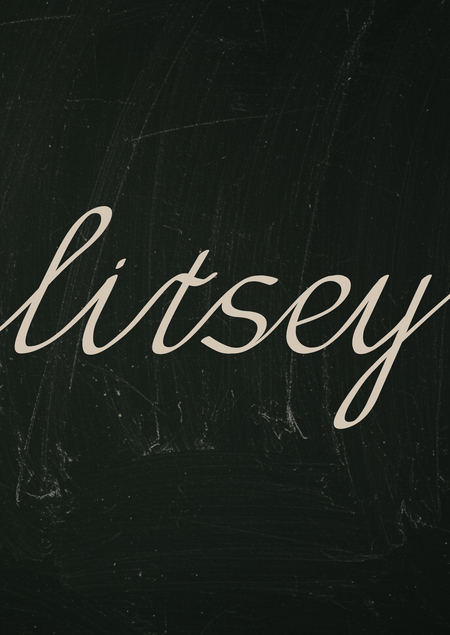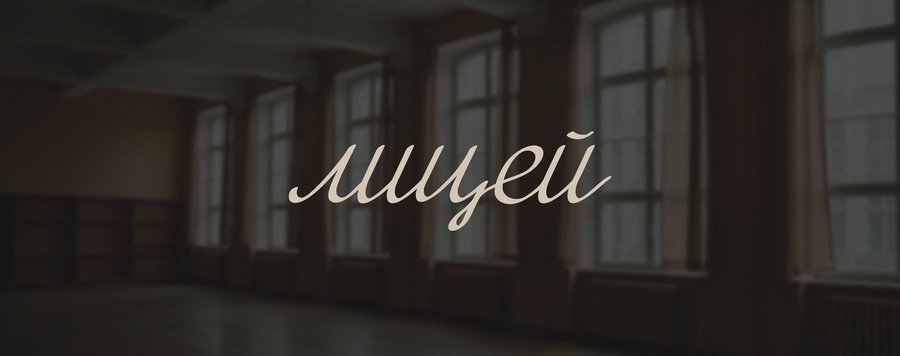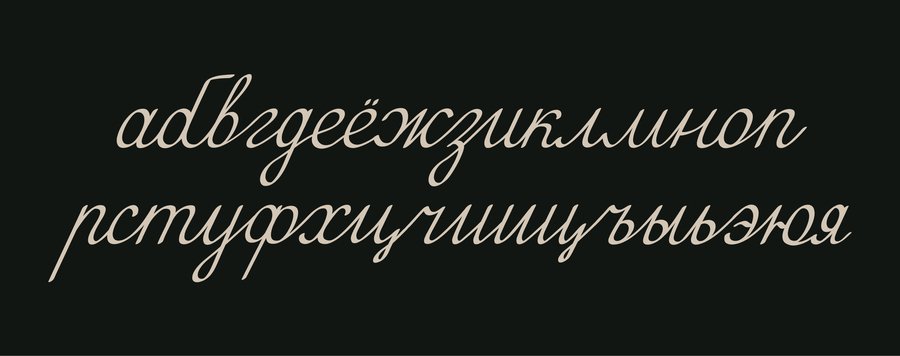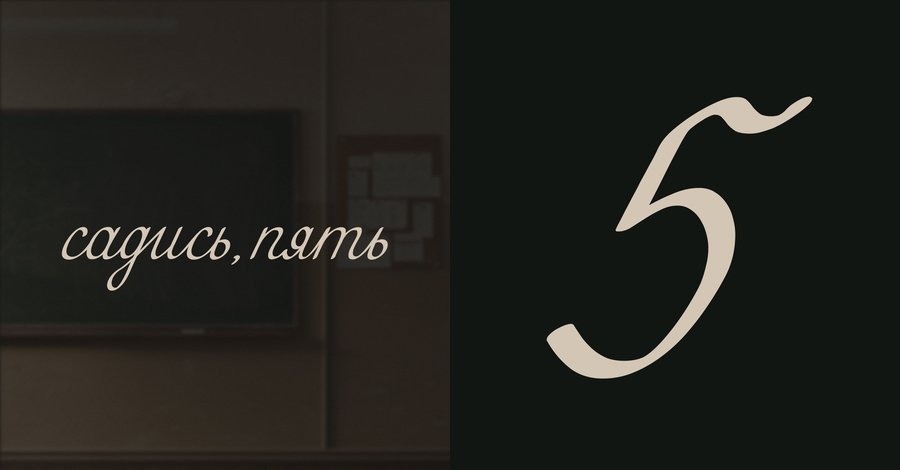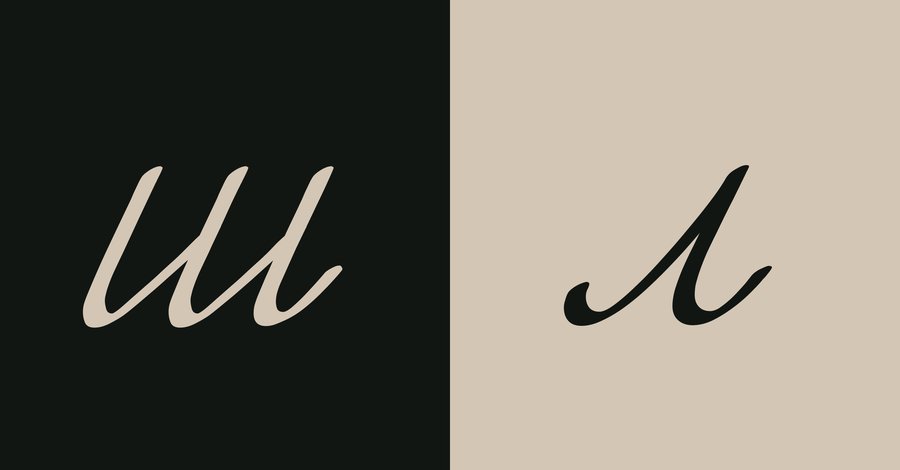
Шрифт «Лицей» создавался глядя на старые школьные прописи, где буквы плавно тянутся, как будто ручка только что прошла по линейке. По своей сути школьный шрифт напоминает ученический почерк, которым учили писать аккуратно, с наклоном.
Он для тех, кто помнит доску, мел и тетрадь с разметкой.